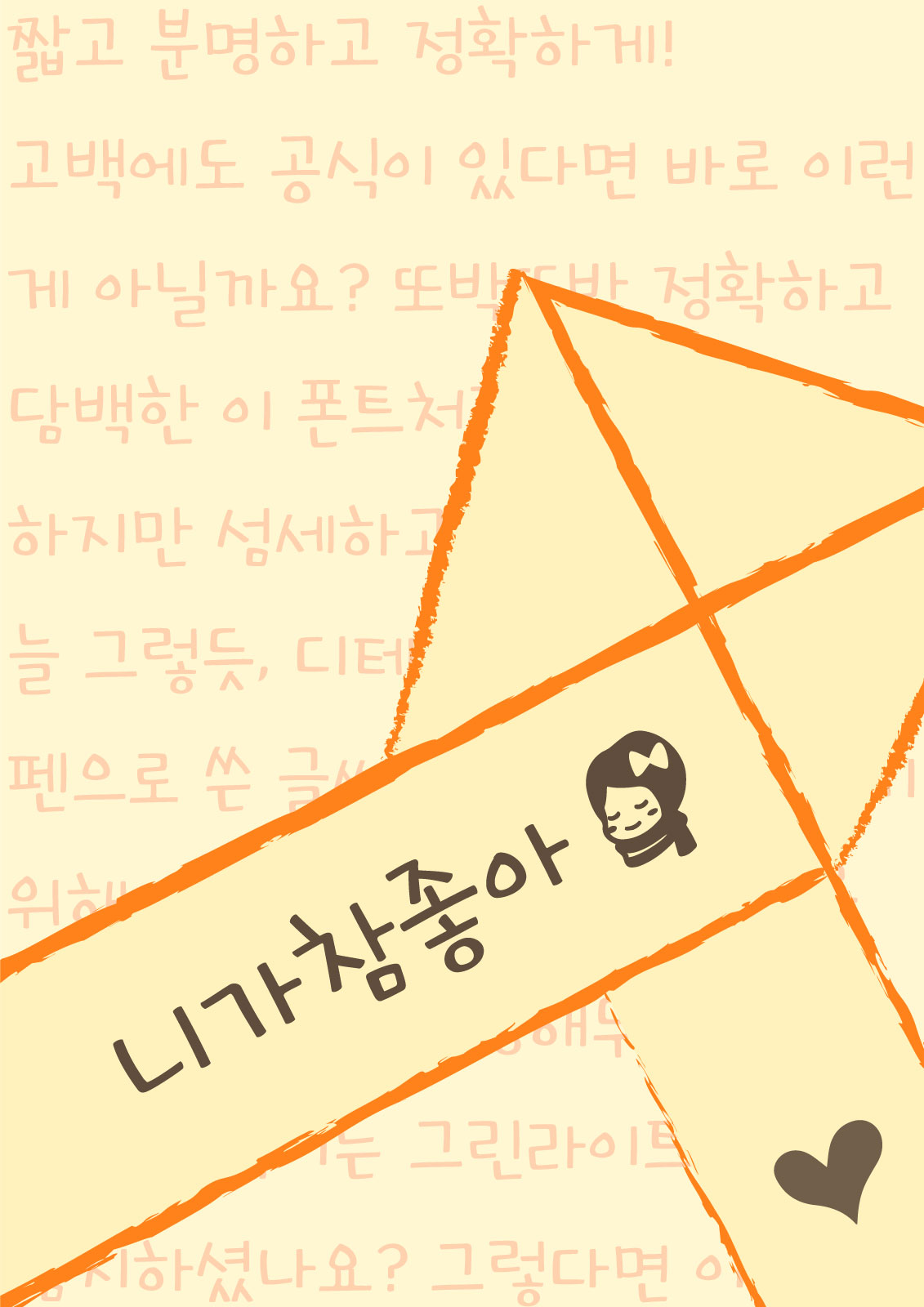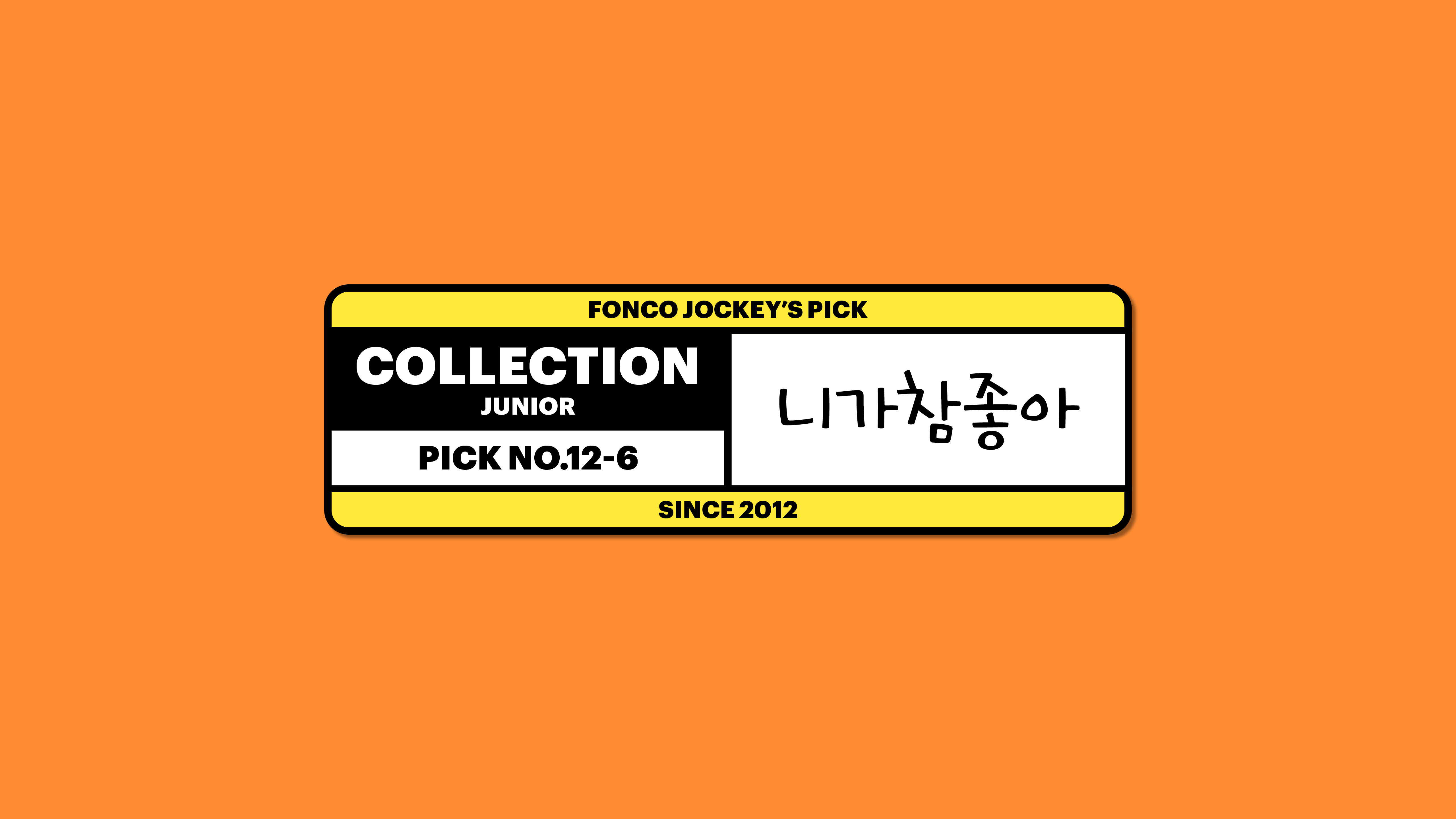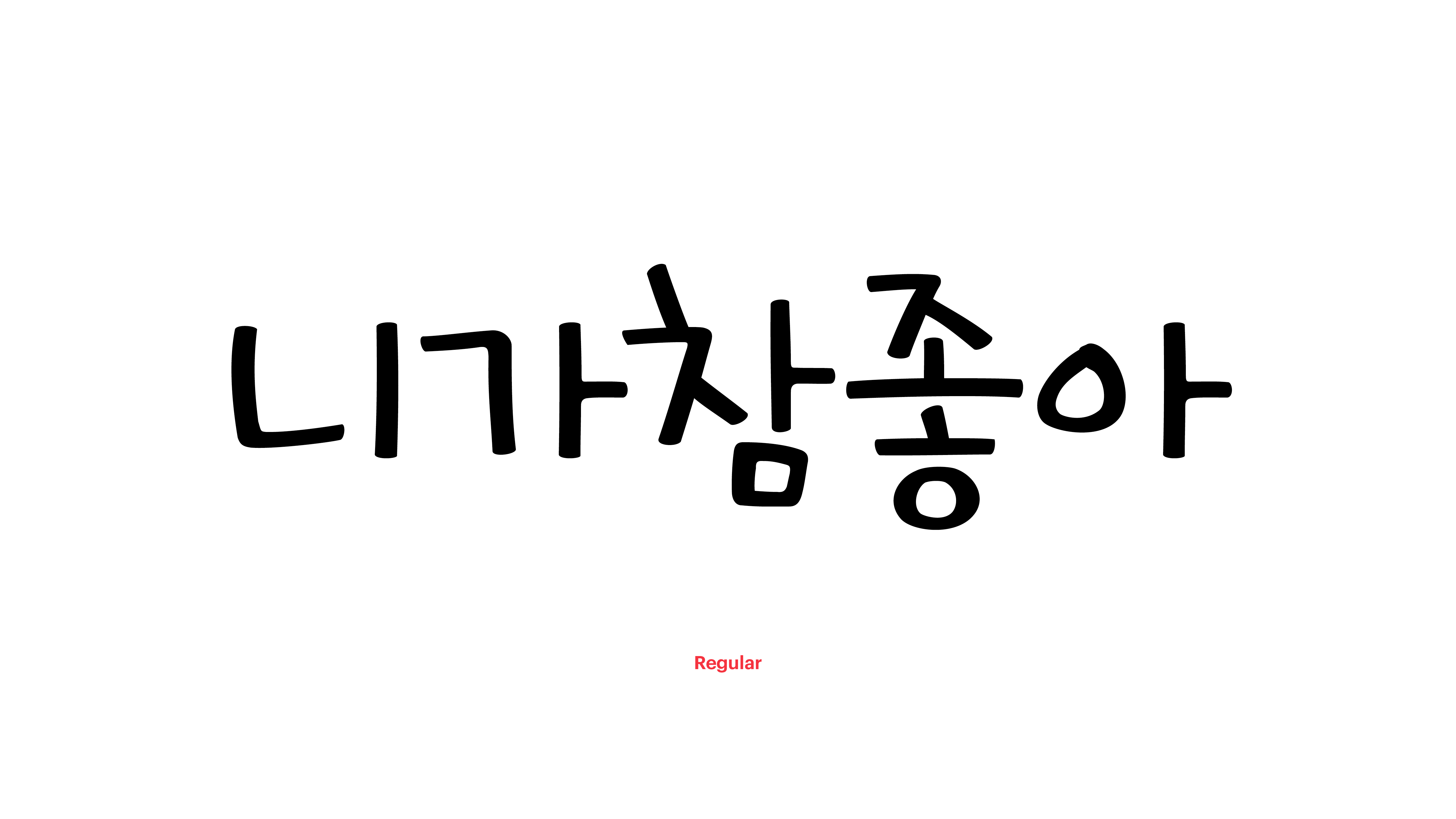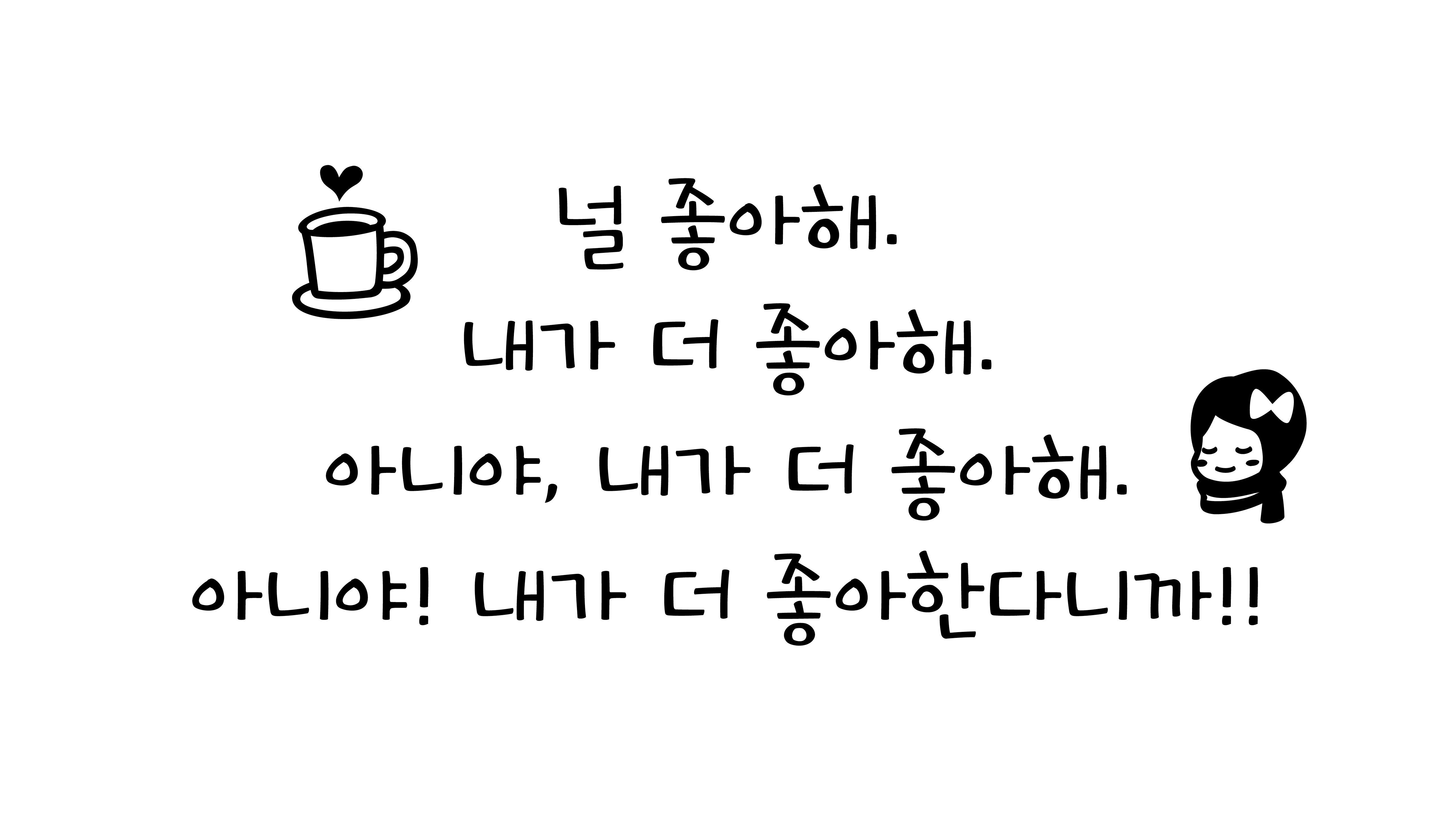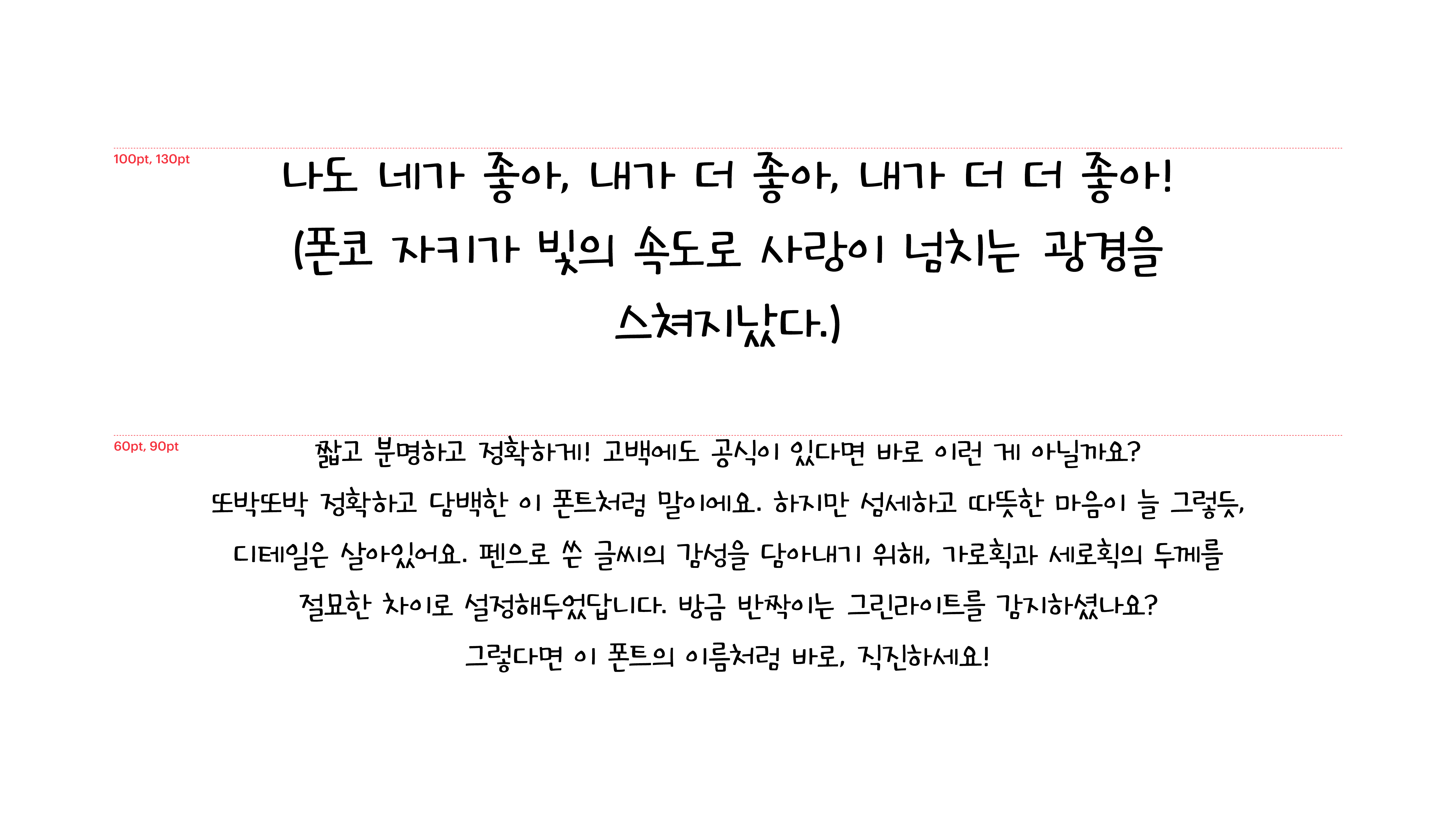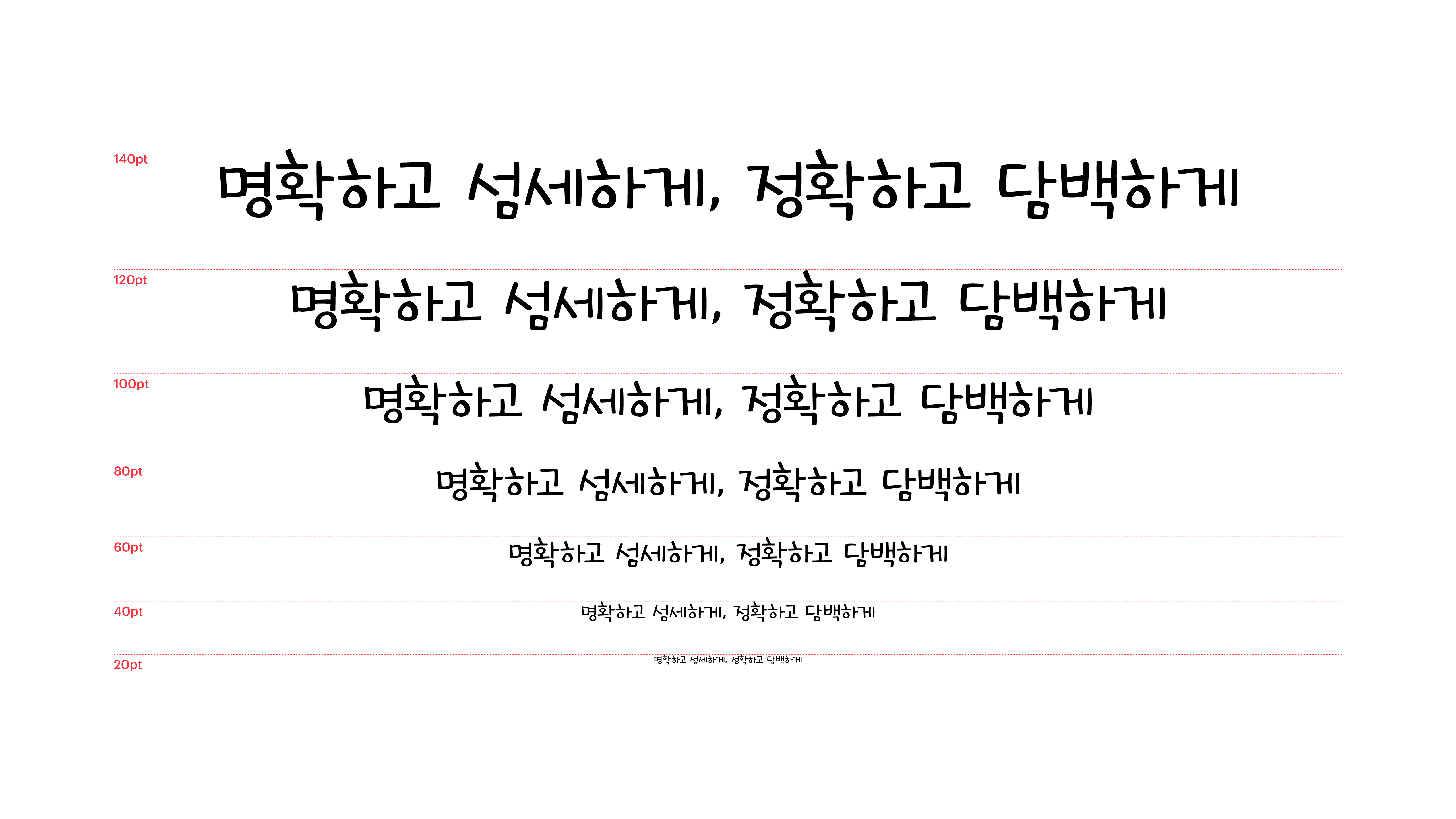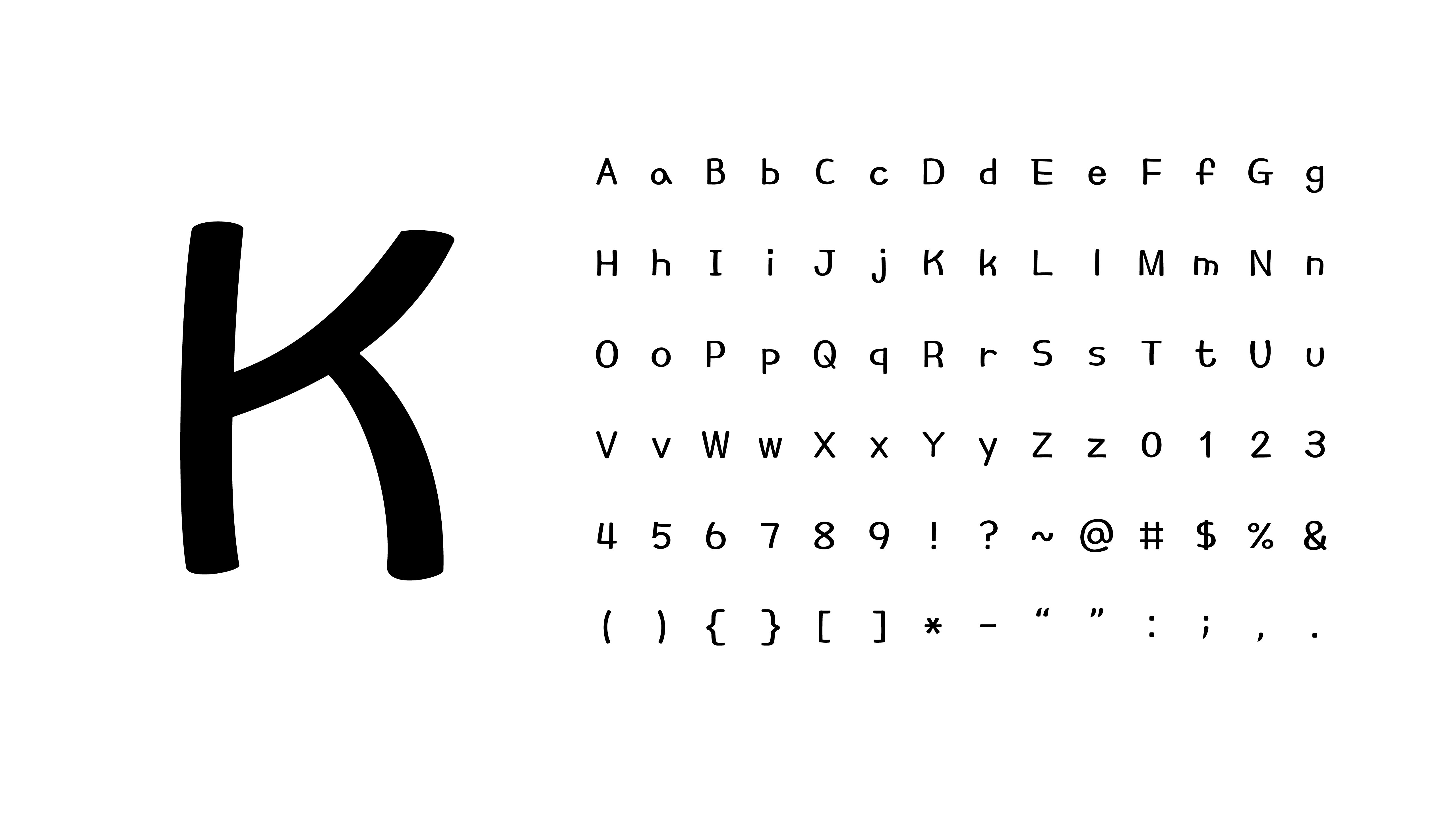
짧고 분명하고 정확하게! 고백에도 공식이 있다면 바로 이런 게 아닐까요? 또박또박 정확하고 담백한 이 폰트처럼 말이에요. 하지만 섬세하고 따뜻한 마음이 늘 그렇듯, 디테일은 살아있어요. 펜으로 쓴 글씨의 감성을 담아내기 위해, 가로획과 세로획의 두께를 절묘한 차이로 설정해두었답니다. 방금 반짝이는 그린라이트를 감지하셨나요? 그렇다면 이 폰트의 이름처럼 바로, 직진하세요!
Yoon 니가참좋아